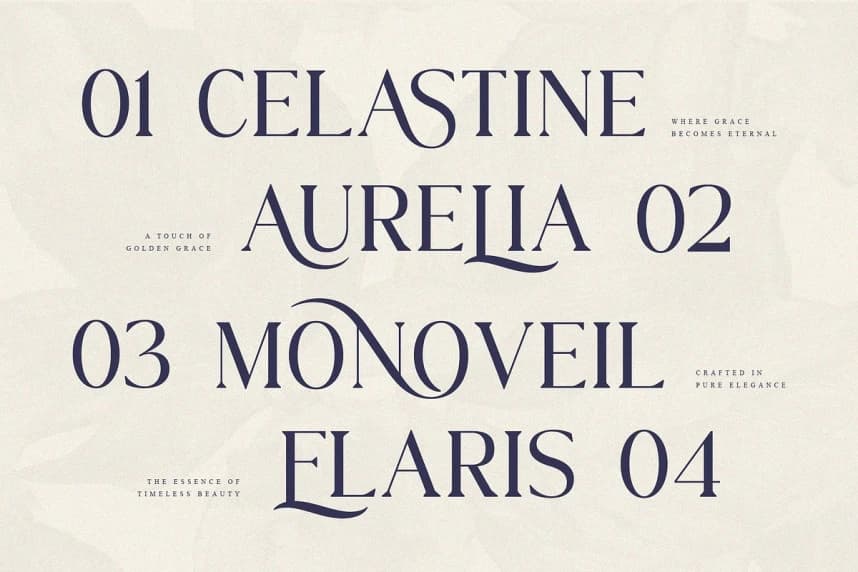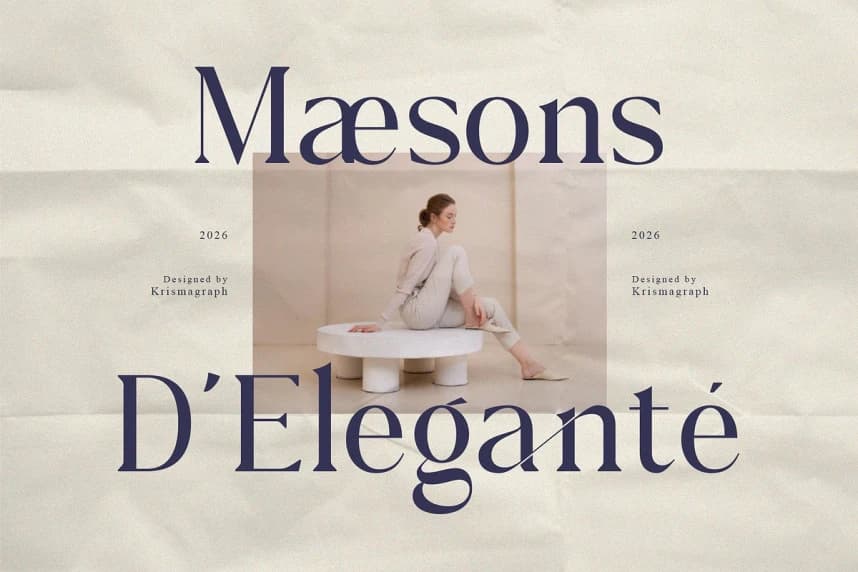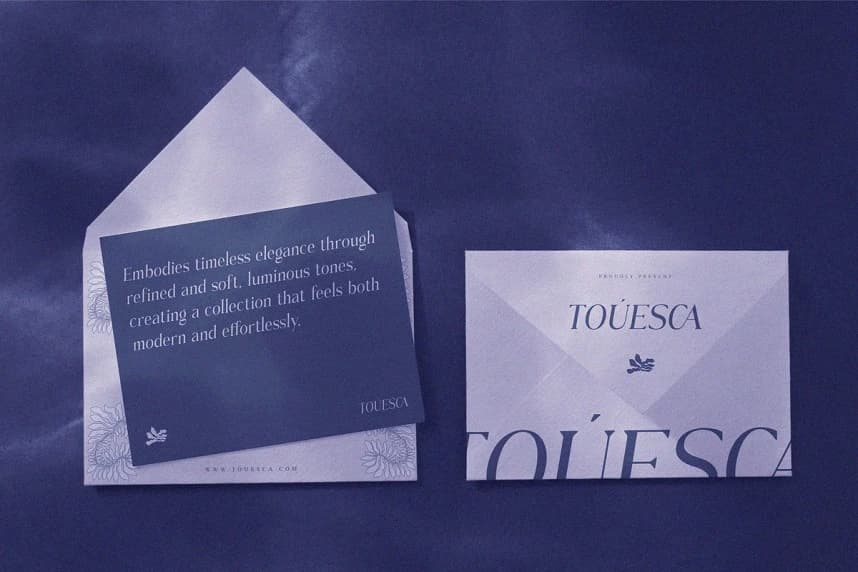
Roslane Font
Roslane Font, sessiz güven ve zahmetsiz zarafeti simgeleyen modern bir yüksek moda gösterişli serif yazı tipidir. Büyük editoryal seriflerin mirasından beslenen bu yazı tipi, bu gelenekleri daha keskin kontrastlar, daha dramatik kıvrımlar ve bu anın tamamen hissedildiği çağdaş bir siluete sahip olac
Roslane Font, modern bir yüksek moda gösterişli serif yazı tipi olup sessiz güveni ve zahmetsiz zarafeti barındırır. Büyük editoryal seriflerin mirasından beslenen bu yazı, daha keskin kontrast, daha dramatik kıvrımlar ve bu anın tamamen hissedildiği çağdaş bir silüete sahip olarak bu gelenekleri inceltir.